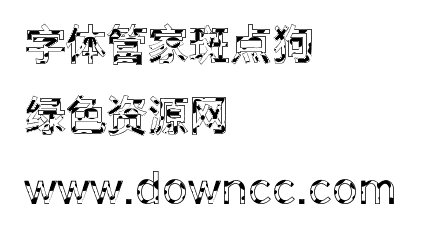
字體管家斑點狗
字體管家斑點狗是一款空心字體,同時在文字中增加不同的黑點,狀死“斑點狗”而命名,讓文字更顯得十分醒目而可愛,快來綠色資源網(wǎng)體驗吧!
字體管家斑點狗字體介紹
字體管家斑點狗以黑體字體為原形,在字體內(nèi)加入斑點圖案,整體結(jié)構(gòu)端正大方,識別性強,同時字庫完整,適用范圍較廣,能滿足用戶日常工作的需求!
斑點狗字體出自字體管家,有著十分時尚顯眼的外觀,讓文字經(jīng)過處理過更加吸引讀者的目光,造型大方而精簡,鏤空的造型也很能贏得大家的好感,可以運用在平面設(shè)計、藝術(shù)設(shè)計、包裝設(shè)計等諸多場合!